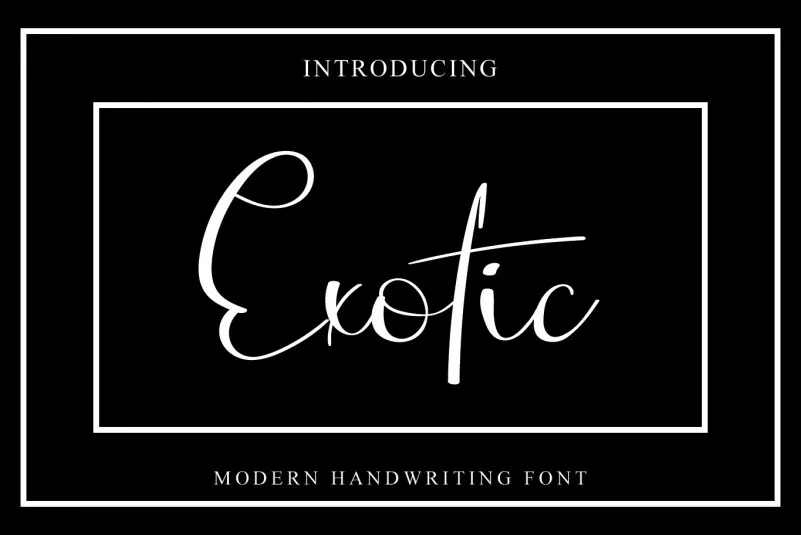
Esta é uma bela tipografia script. Ela foi cuidadosamente feita com muito detalhe. Independente do assunto, essa fonte se tornará um maravilhoso ativo para seu acervo de fonts, pois tem a capacidade de iluminar qualquer criação. Seja ela um documento profissional, uma obra de arte digital ou até mesmo um projeto gráfico pessoal, esta font poderá adicionar um toque único e encantador a seu trabalho. Se você está procurando por uma font que não apenas se destaca no campo da escrita, mas também na sua capacidade para transformar pequenos elementos em algo extraordinário, essa é uma ótima escolha. Escolha “Exotic Font” de Erik Studio e transforme suas ideias em obras únicas.